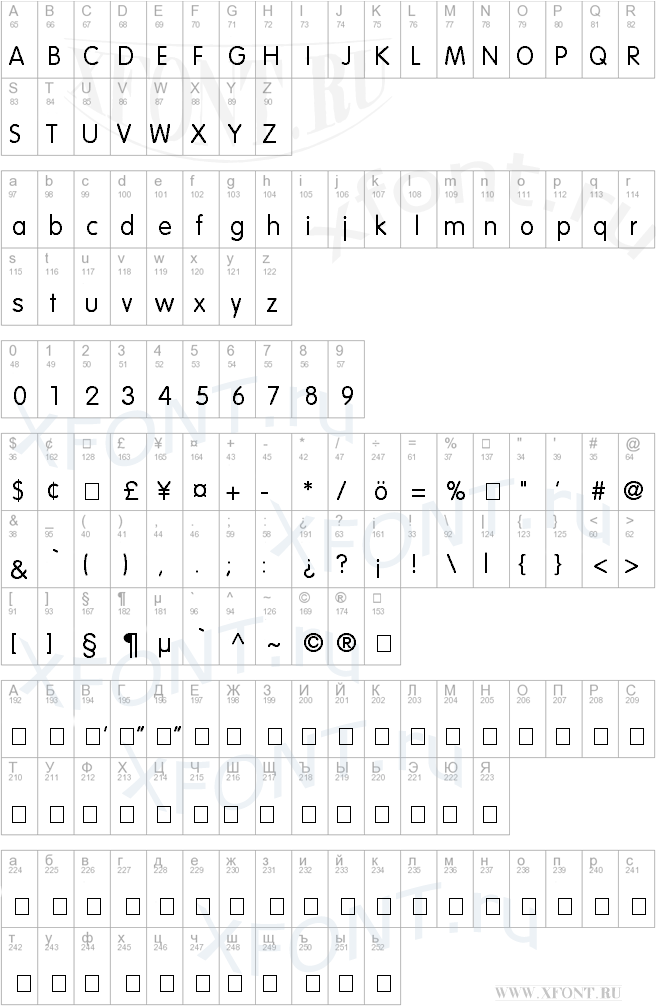
![]() 21 сент. 2018 г. Здесь Вы можете бесплатно скачать шрифт Vogue разработанный Vladimir Nikolic, протестировать его и посмотреть таблицу символов. Vogue Font FREE Download | Hyperpix![]() Vogue Bold · Характеристики шрифта · Скачать шрифт Vogue Bold · Поделиться с друзьями. ВКонтакте · Одноклассники. Minimalistische Schriftart, Stylish Font, Logo Schriftart.![]() Arapey (Ah-ra-pay) is a contemporary modern typeface with some features of a Bodoni, but the structures, soft lines, and finishes leave a calm and. Шрифт Vogue Paris: Скачать И Установить На WEB Сайт![]() 1 сент. 2017 г. Download the Vogue Cyr Bold free font. Detailed information on the Vogue Cyr Bold font: ✓ license; ✓ glyphs; ✓ specimens. Vogue | XFont.Ru - Шрифты, Скачать Шрифт Бесплатно![]() Шрифт Vogue с начертанием Regular относится к семейству Vogue. Примеры написания Vogue Regular можно посмотреть на сайте шрифтов AZFonts. Дизайнер шрифта — нет. Vogue Highline Sans & Serif By Letterhead Foundry, Russia. To Be.![]() Download Vogue Paris font together with @font-face CSS styles for website or graphic editors (Photoshop, Figma, Sketch, Adobe InDesign) Vogue Highline Sans And SerifСкачать шрифт Vogue Paris вместе с @font-face CSS стилями для сайта или графических редакторов (Photoshop, Figma, Sketch, Adobe InDesign. Vogue Font Family Download - Colaboratory![]() 4 окт. 2023 г. Скачать шрифт So Vogue. Шрифт доступен во всех форматах (So Vogue woff2, So Vogue woff, So Vogue ttf, So Vogue eot) и применим для веб-сайта. Vogue Highline Sans Font,VogueHighlineSans Font|Vogue Highline.![]() Шрифт Vogue, лицензия и условия использования, символы, категории, поддерживаемые языки, ссылка для скачивания. Vogue Font - Download Free Font![]() Шрифт Vogue Bold. Скачать шрифт Vogue Bold Тип шрифта: TrueType. Стиль гарнитуры: Рубленый Название гарнитуры: Vogue PostScript-имя: VogueBold Vogue Шрифт![]() Семейство шрифтов Vogue, разработанное Vladimir Nikolic, имеет в общей сложности 1 различных стилей. Вы можете загрузить шрифт Vogue на свой компьютер или. Vogue Bold Font Free Download - Colaboratory![]() Download free vogue font, view its character map and generate text-based images or logos with vogue font online. Schriftart Vogue - Download![]() Шрифт Vogue Regular. Размер файла: 25.86 KB. Скачайте бесплатно в один клик. Также вы можете посмотреть как выглядит шрифт онлайн и добавить его в. Vektor-Helle Neon-Vorlage Elegante Vogue Electric Light Font.![]() 11 апр. 2019 г. Мы отобрали 185 шрифтов вместе с редакцией журнала «Шрифт. Vogue Highline Serif by Yuri Gordon (Letterhead Studio. WF-Regular. Статьи На Тему: Инновации — Друкарня New Media Страница 3.![]() 19 окт. 2020 г. Скачать шрифт Vogue Paris для Figma, Web сайта и Photoshop во всех начертаниях. Vogue Regular Font - Colaboratory![]() 16 июн. 2020 г. Jun 16, 2020 - Find hd Vogue Logo Png , Png Download - Vogue Font, Transparent Png. To search and download more free transparent png images. Шрифт Vogue Paris Скачать Для Web, Figma Или Photoshop.![]() Free Download Vogue Font file in TTF font type, (vogue.ttf) from Basic category with the Serif style. Download TrueType font for using on design projects and. Vogue Magazine Fonts Download - Colaboratory![]() 23 окт. 2019 г. @font-face { font-family: "Vogue Highline Serif Medium"; src: url(" Vogue Highline Sans & Serif By Letterhead Foundry, Russia. To Be.![]() 1 сент. 2017 г. Скачать шрифт Vogue Normal бесплатно. Подробная информация о шрифте Vogue Normal: ✓ лицензия; ✓ глифы; ✓ примеры; ✓ для ОС: Windows. Vogue Font FREE Download | Hyperpix![]() Vogue Cyr [Rus by me] Bold шрифт вы можете скачать на этой странице версии Version 1.00 December 23, 2018, initial release, который относится к семейству. | ||